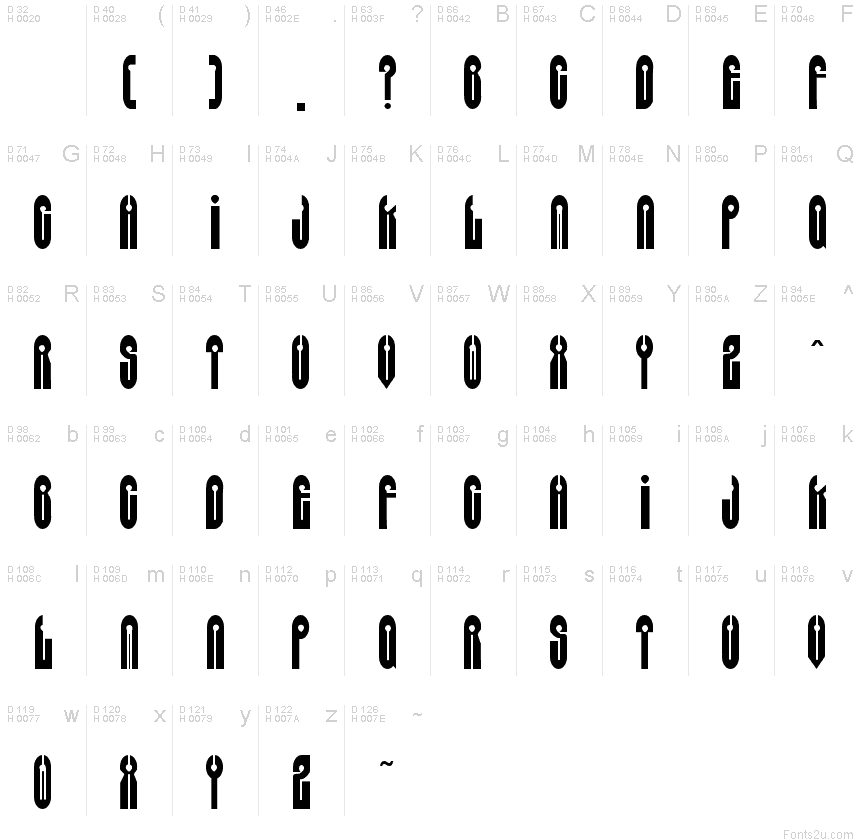
Grey(Alien)SW od Astigmatic One Eye je futuristické displejové písmo, které je zdarma. Jeho vysoká, monolitická písmena působí, jako by byla vytesána do trupu vesmírné lodi, a díky otvorům ve stylu klíčových dírek a přísným vertikálním řezům získává každé slovo tajemný, kódovaný vzhled. Rytmus je těsný a téměř mechanický, takže řádky textu do sebe zapadají jako mimozemské glyfy, přičemž si stále zachovávají čitelnost i ve větších velikostech.
S Grey(Alien)SW získají nadpisy a loga okamžitě sci-fi nádech z jiného světa, což se skvěle hodí pro obaly her, filmové plakáty, akční letáky, technologický branding, ziny nebo experimentální obaly alb. Toto bezplatné písmo vynikne, když ho necháte vyniknout ve velkých, výrazných nadpisech a zkombinujete ho s čistým, geometrickým bezpatkovým písmem pro doplňující text.